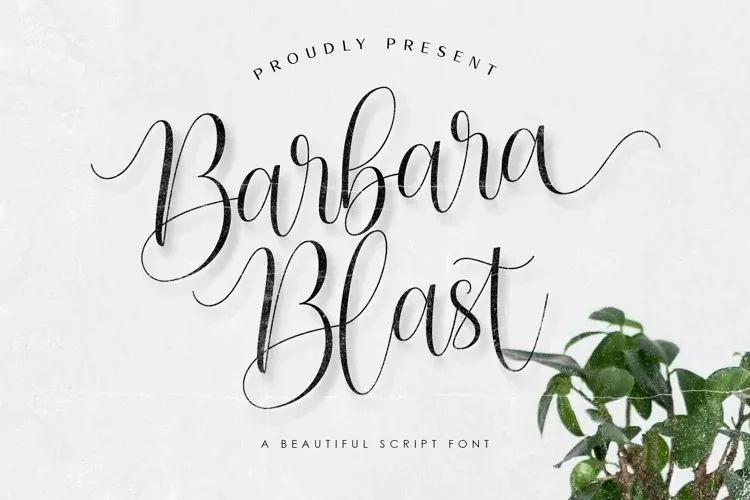
Barbara Blast Font – Download Grátis
A Barbara Blast Font é uma elegante tipografia de script moderna que resulta de um encontro entre a velha arte do pen & lápis e o novo mundo da esferográfica. Desenhada para designers versáteis, essa fonte não só oferece um estilo único e distintivo, como também traz ao seu design uma variedade impressionante de caracteres que permitem inúmeras possibilidades criativas. Suas linhas delicadas e sua capacidade de se adaptar a muitos idiomas tornam-a perfeita para projetos variados, desde identidades corporativas até logotipos e artes digitais. E por não contar apenas com o inglês, Barbara Blast também suporta múltiplas línguas, incluindo alternâncias estilísticas e ligaduras complexas que a tornam ainda mais versátil. Sem dúvida, essa font é um must-have para qualquer designer em busca de uma mistura única entre tradição e modernidade.